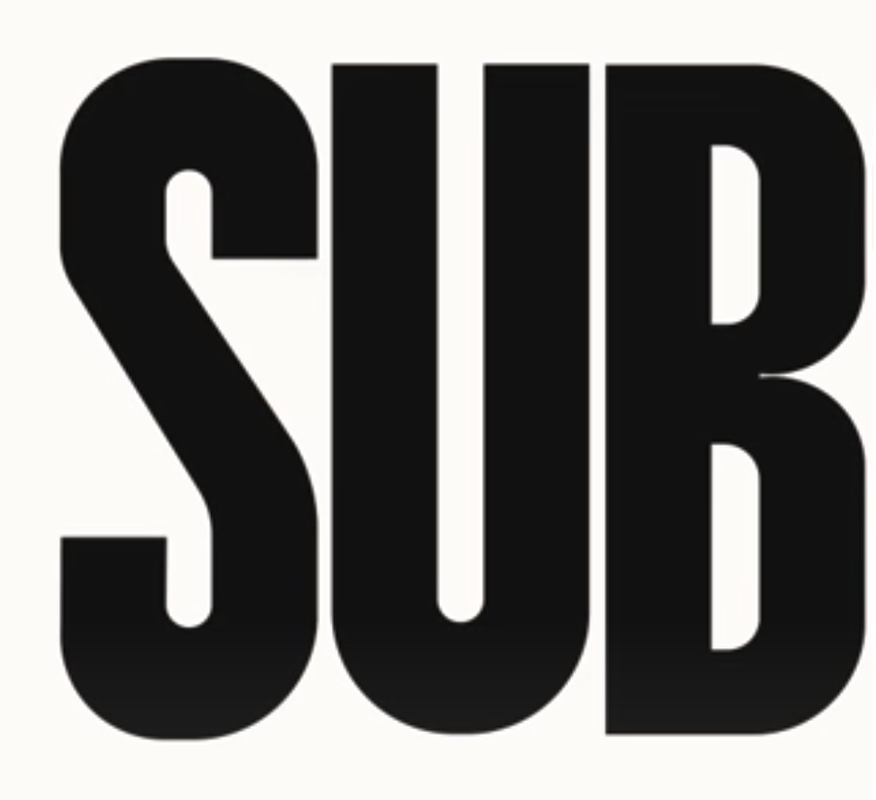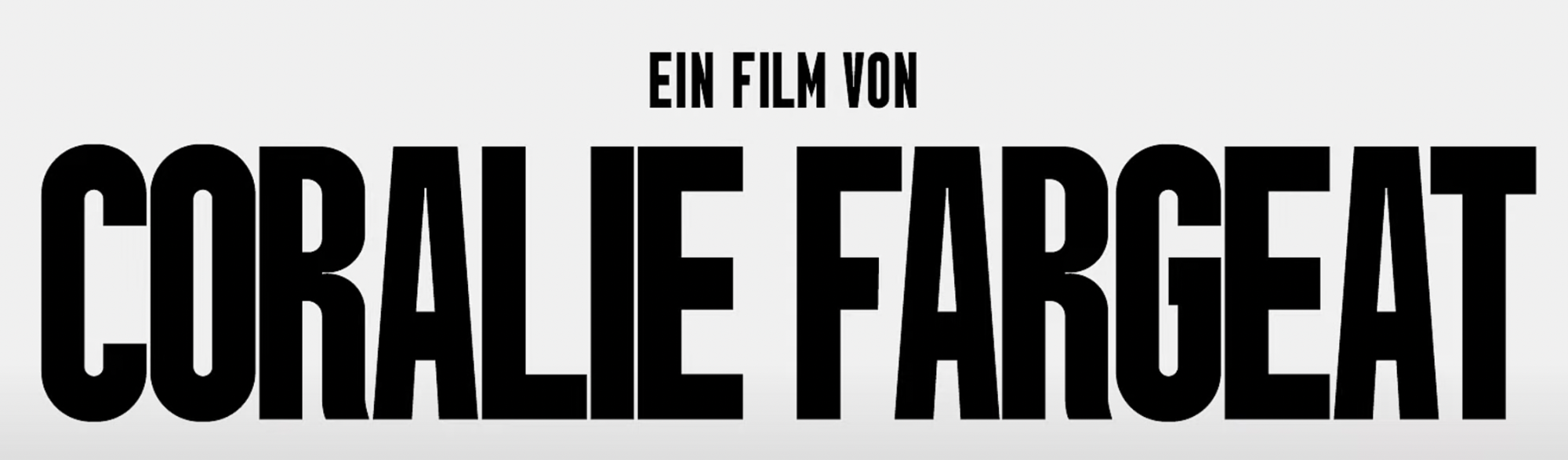
Kinofilm Substance - Verwendete Typo im Trailer
kann jemand von Euch mir sagen wie die Schrift heisst?
Whatthefont gibt leider auch kein mir passendes Ergebnis.
Ich rate mal …
Ein Film von -> Bebas (Kai)
Coralie Fargeat -> Bebas Neue Bold (eingefettet)
Bebas Neue von Flat IT:
Bebas Kai von Dharmatype:
Die Schriften sind verwandt, aber M und R unterscheiden sich …
Mit Bebas hat die gesuchte Schrift nicht viel gemein.
Die Buchstabenproportionen der Schrift sind schon sehr eigen. Das E ist viel zu breit; die Bögen des R wirken unharmonisch etc. Aber letztlich sind das genau die Elemente, die der Schrift ihre Eigenständigkeit geben. Ich kann mir daher auch vorstellen, dass die Schrift exklusiv für den Film (und die Bewerbung dessen) entworfen wurde.
Dann wäre sie vermutlich auch auf den Plakaten verwendet worden, dort ist’s aber eine ähnliche andere:
Die gesuchte ist schon sehr eigen, auch die Tintenfalle bei R und B …
Genau diese Inktraps und auch der "ruppige" Aufbau gefällt mir so gut und würde gerne die Font kaufen. Finde Sie aber nicht. Habe gerade einige Hersteller abgesucht leider nichts gefunden.
Es sind aber auch andere Plakate mit der Schrift erstellt worden: